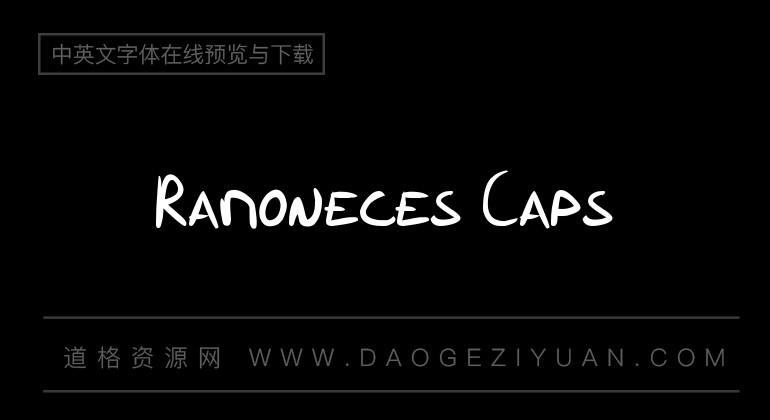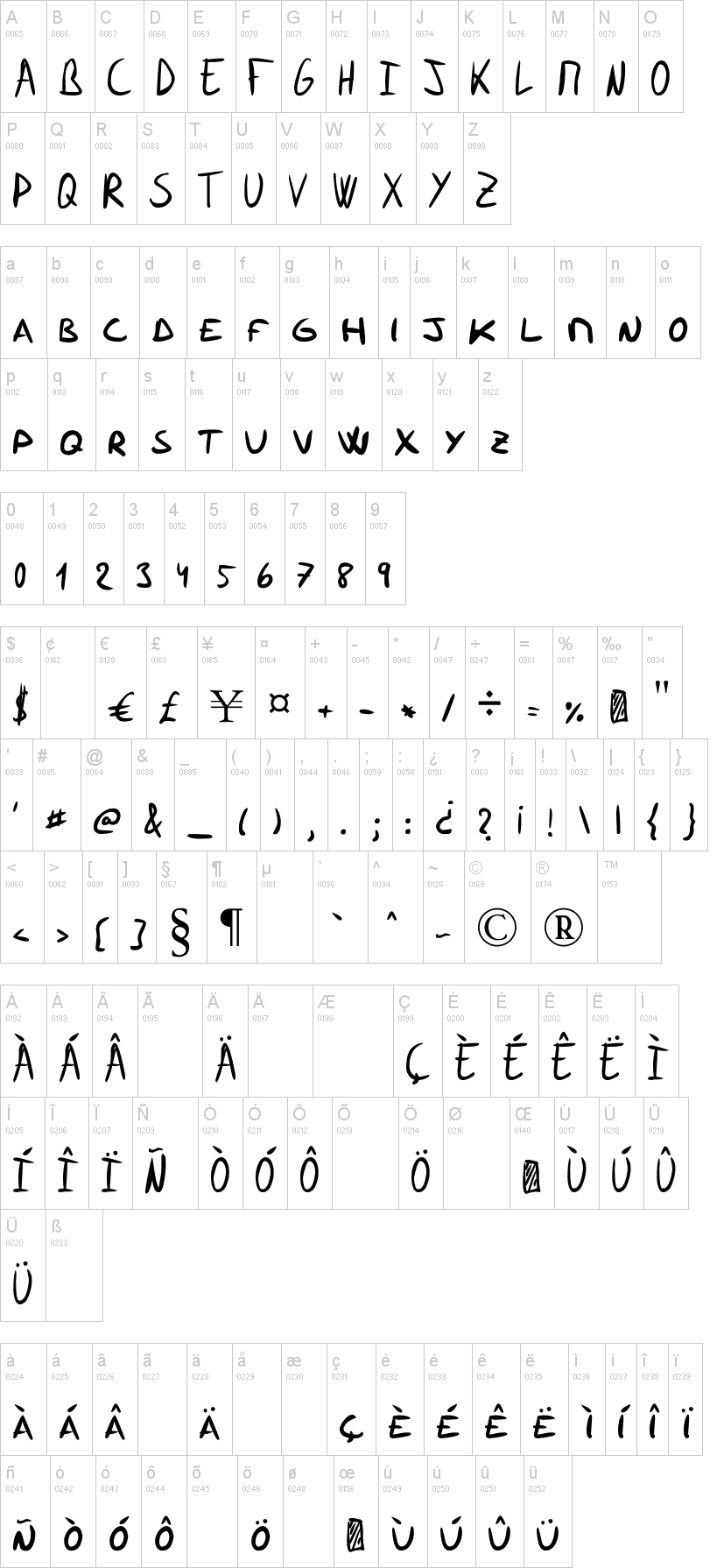
Ramoneces Caps
Ramoneces Caps是一款经典的英文字体,它的字形优雅而清晰,采用细长的笔画、比例秩序的构造,使得它的字体看上去精美而简洁。它的字体比例也很标准,特别适合用于各种设计作品,如广告、海报、网页等。由于它的英文字体比较细长,所以也可以用于更小的文字,比如标签或标题等。
Ramoneces Caps是一款非常不错的手写艺术字体,具有很好的视觉感,适合于文化类的宣传设计、商业类品牌的广告和产品包装设计以及个性化文字排版等较多场景。